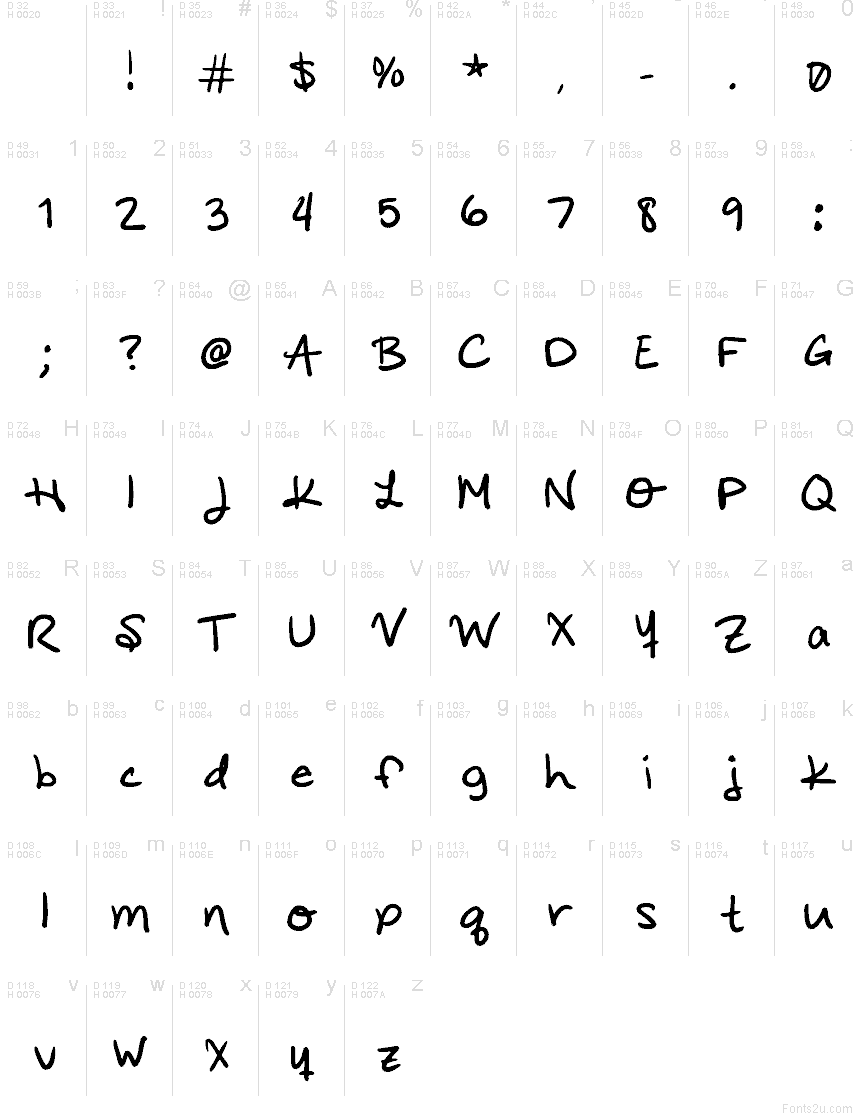
Noteshand Regular
Noteshand es una tipografía manuscrita gratuita con un aire espontáneo, como si de una nota personal se tratara. Las letras parecen escritas de forma rápida en lugar de cuidadosamente calrafiadas, con una leve oscilación, formas redondeadas y un ritmo ligeramente irregular que le aporta un toque humano y casual.
Esto convierte a esta fuente gratuita en una elección natural para títulos de álbumes de recortes, branding de estilo diario, menús de cafeterías, destacados en envases y publicaciones en redes sociales que necesiten una voz personal. También funciona muy bien para titulares cortos y tarjetas de título, ya que sus trazos amplios y sencillos mantienen el ambiente manuscrito directo y sin complicaciones.
Es un reflejo de mi propia letra, tal y como la encontrarías en un cuaderno.